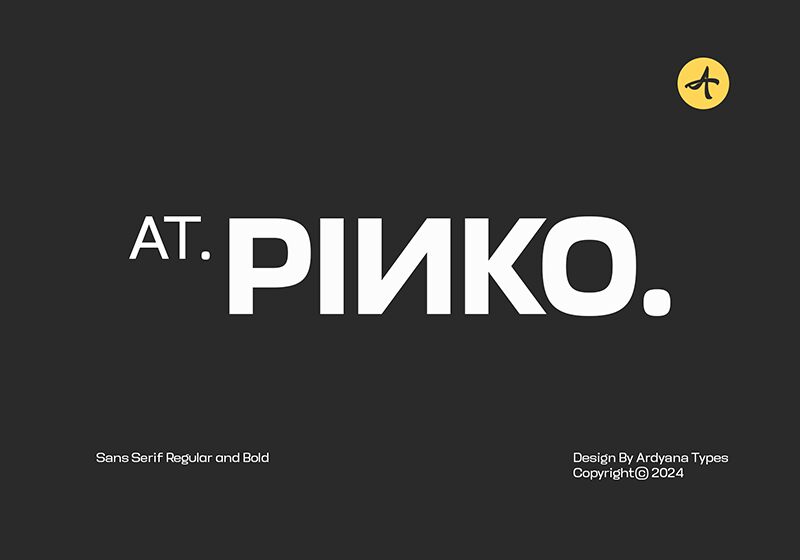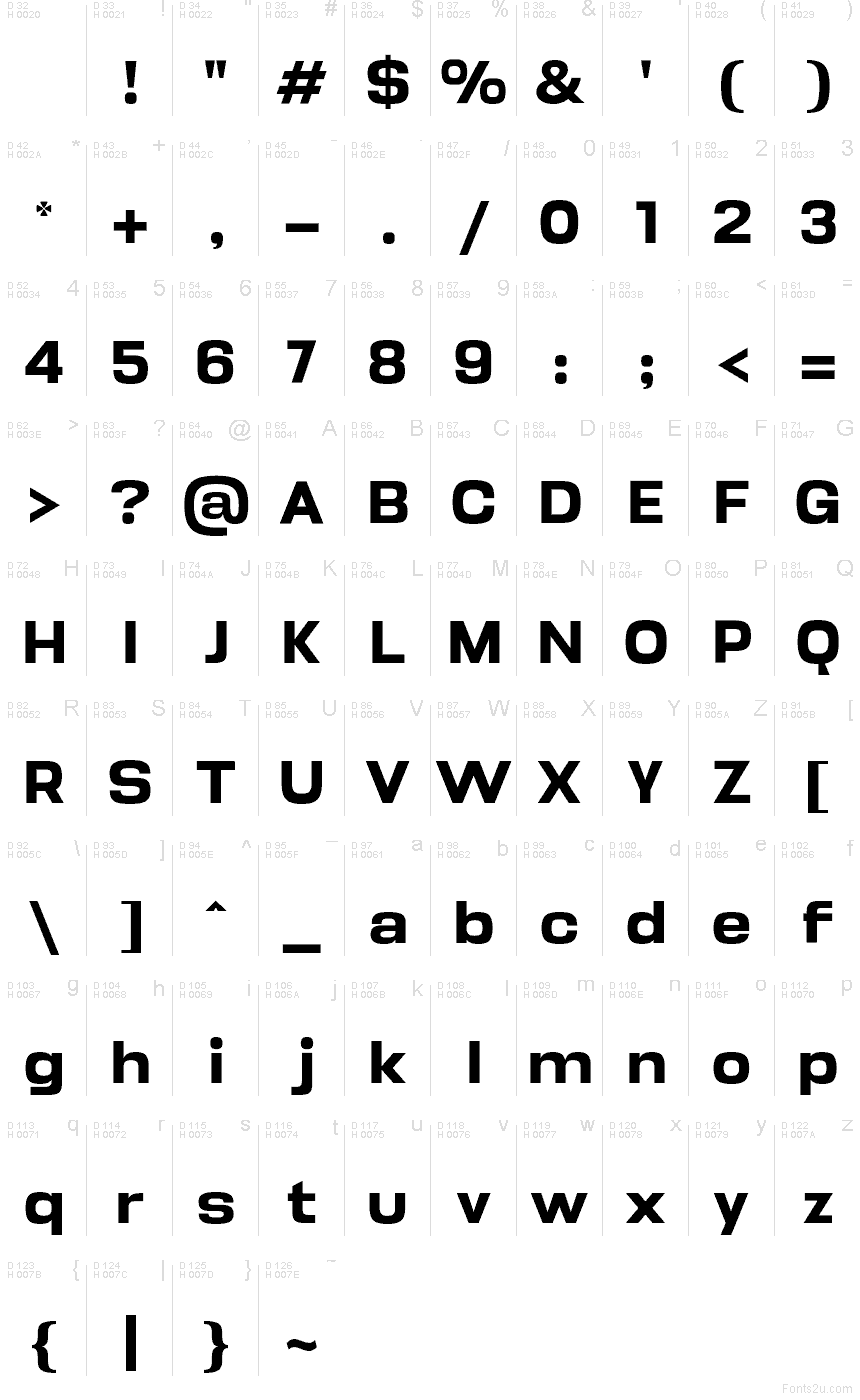
Písmo AT Pinko Bold od Ardyanatypes je bezpatkový font zdarma s pevnými geometrickými tvary a jemně zaoblenými rohy. Široké tvary a kompaktní rozestupy dodávají písmu solidní a vyvážený rytmus, který však nepůsobí strojeně.
AT Pinko Bold skvěle funguje v nadpisech plakátů, logotypech, obalech, názvech aplikací a krátkých redakčních akcentech, kde bezpatkové písmo potřebuje trochu více výrazu. Tento font zdarma se také hodí pro branding, značení, grafiku na sociální sítě a produktové nadpisy, protože jeho jednoduchá struktura drží čistý vzhled i v krátkých, úderných textech.